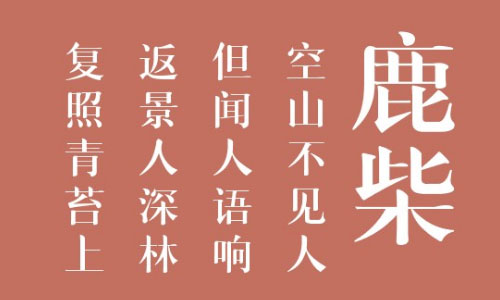
南構(gòu)線(xiàn)新宋字體是一款非常不錯(cuò)的印刷風(fēng)格字體,字體結(jié)構(gòu)醒目,簡(jiǎn)潔大方,非常有特色,能夠適用于藝術(shù)設(shè)計(jì)、包裝印刷、簽名設(shè)計(jì)、圖形設(shè)計(jì)等領(lǐng)域,歡迎有需要此字體的朋友前來(lái)下載使用。